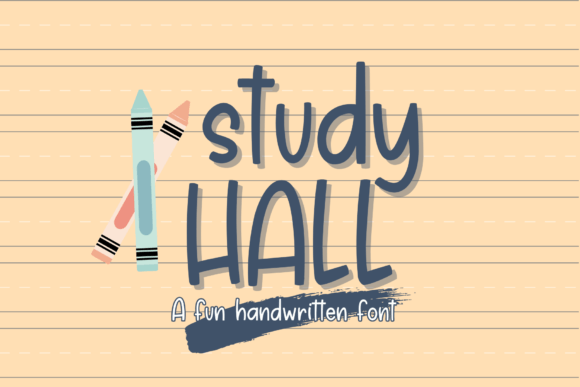
Study Hall
適切なデザイン要素を見つけるのは難しい場合がありますが、Study Hallは作品を即座に引き立てる優れたコレクションを提供します。
POD(オンデマンド印刷)製品、結婚式の招待状、またはソーシャルメディアのグラフィックを作成している場合でも、Study Hallは理想的です。